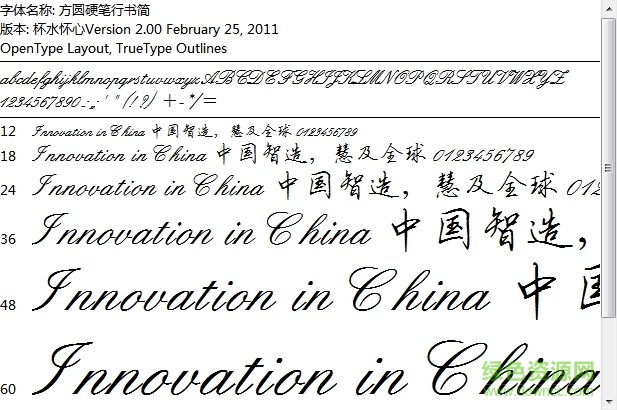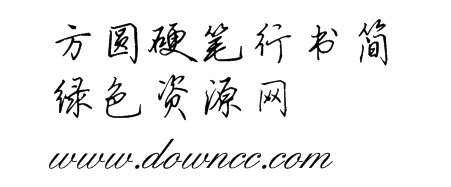
方圓硬筆行書(shū)體是一款非常出色的行書(shū)簡(jiǎn)體,字跡清爽有力,書(shū)寫(xiě)流暢運(yùn)筆細(xì)膩,給文字更加清晰的呈現(xiàn)和閱讀下坡過(guò),喜歡的朋友就來(lái)綠色資源網(wǎng)收藏吧!
方正硬筆行書(shū)簡(jiǎn)字形飄逸大方得體,整體效果非常的出眾,線條粗細(xì)適中,是一款應(yīng)用于廣告設(shè)計(jì)方面的中文行書(shū)字體,可用于藝術(shù)設(shè)計(jì)、包裝印刷、簽名設(shè)計(jì)、圖形設(shè)計(jì)等領(lǐng)域!
方圓硬筆行書(shū)字跡兼具行書(shū)字體與硬幣書(shū)法字體的美好體態(tài),給人活潑而不失沉穩(wěn)的閱讀體驗(yàn),很有古風(fēng)字體的風(fēng)格魅力。